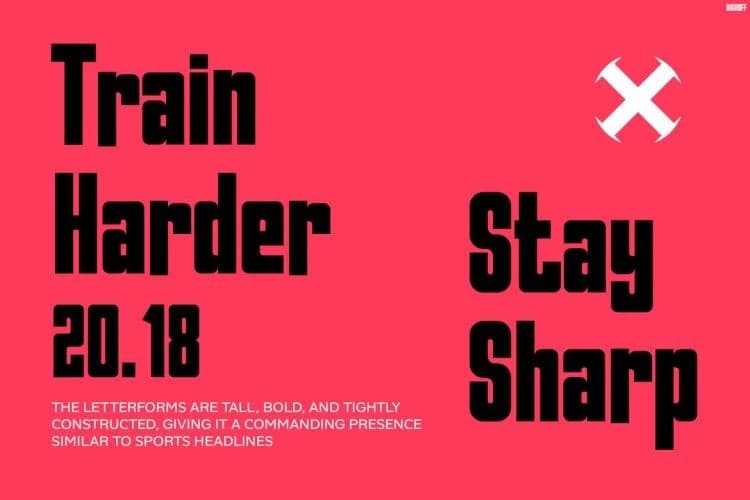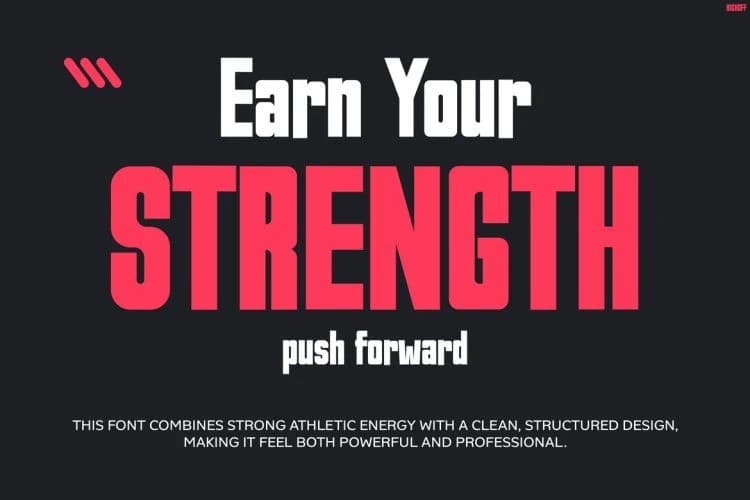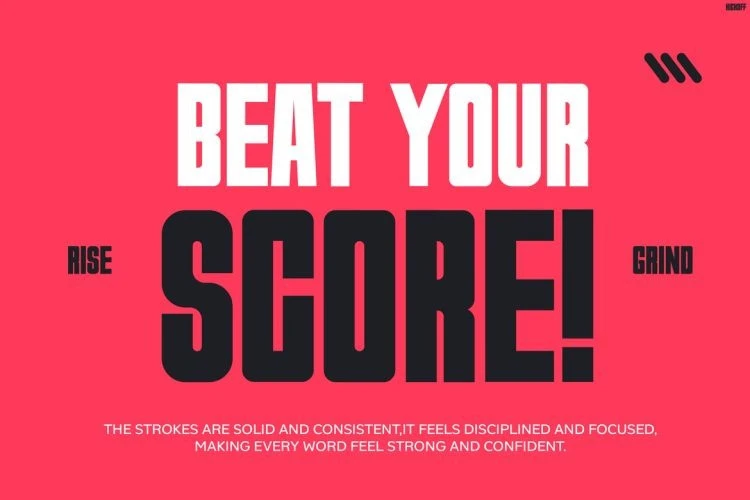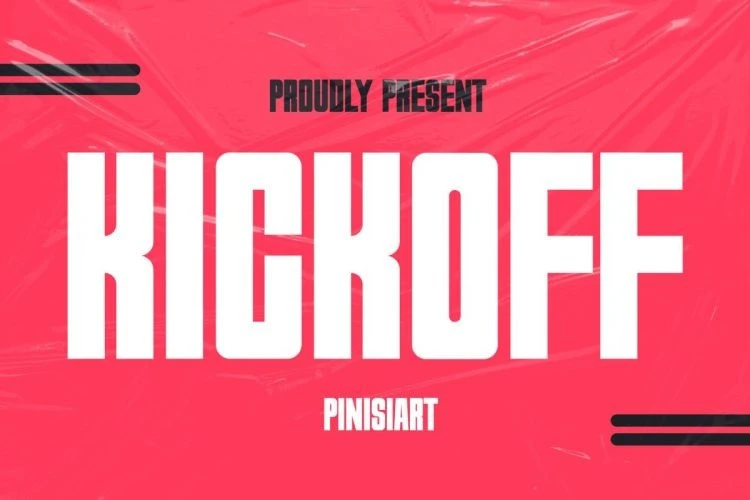
Kickoff Font
KICKOFF Font, dikkati anında ele geçirmek için tasarlanmış güçlü ve yüksek etkiye sahip bir gösterim yazı tipidir. Ayrıca, uzun ve sıkıştırılmış harf biçimleri ile keskin kenarları çarpıcı ve modern bir atletik estetik yaratır.
KICKOFF Font, anında dikkati üzerine çekmeyi hedefleyen güçlü, etkili bir gösteri tipi yazı tipidir. Ayrıca, uzun ve sıkıştırılmış harf biçimleri ile keskin kenarları çarpıcı ve modern bir atletik estetik yaratır.